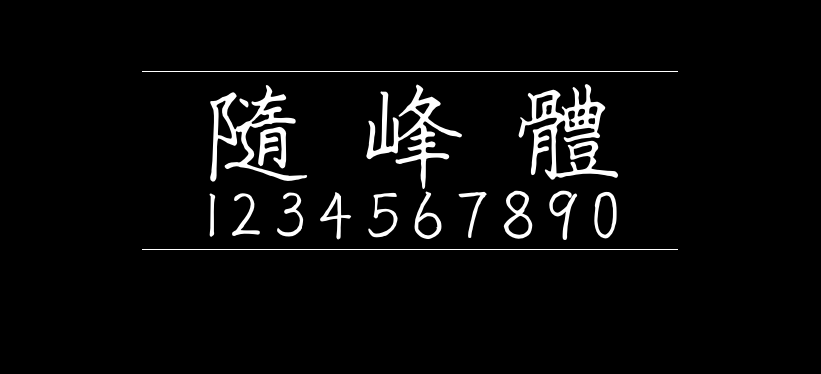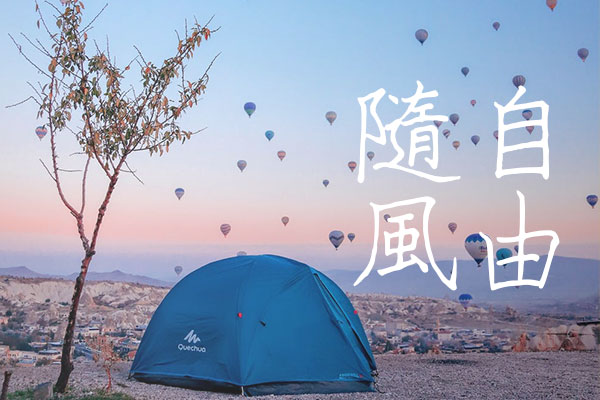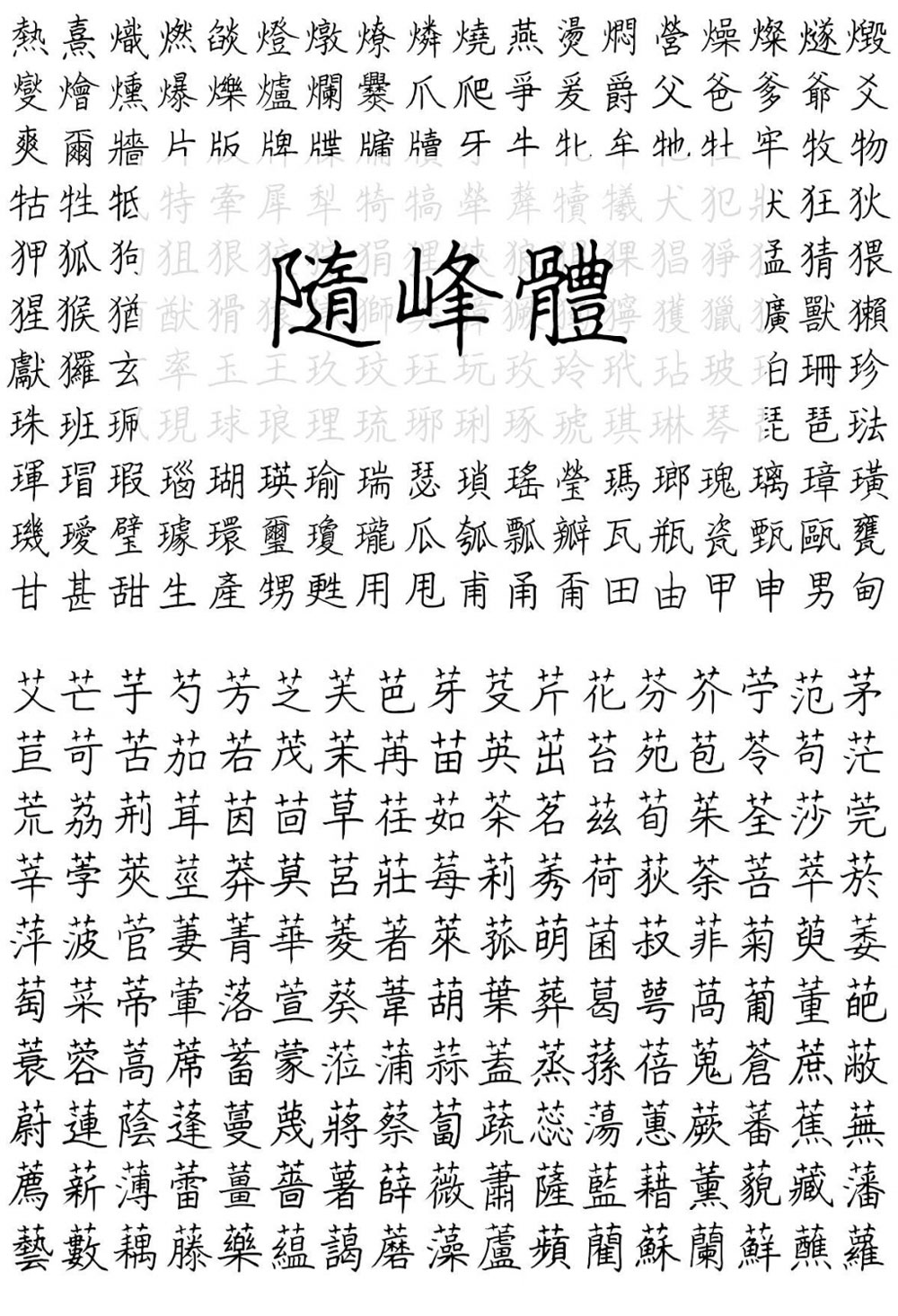
随峰体
随峰体(隨峰體)的创作者是阿坤,一位热爱写字的香港人。“随峰体”是经过两年时间,逐字逐字以啫喱笔写成的手写字体,而且保留手写痕迹和瑕疵。早在一年前就决定以开源形式释出字体,完全免费,可以自由商用,希望大家喜欢。Beta版推出之后,会根据用家意见不断完善字体,以及统一字体风格后,再同样以开源形式推出正式版,敬请期待!
字数大约6100(包括数字、英文、标点符号),繁体中文支持得不错,简体则存在缺字的现象。